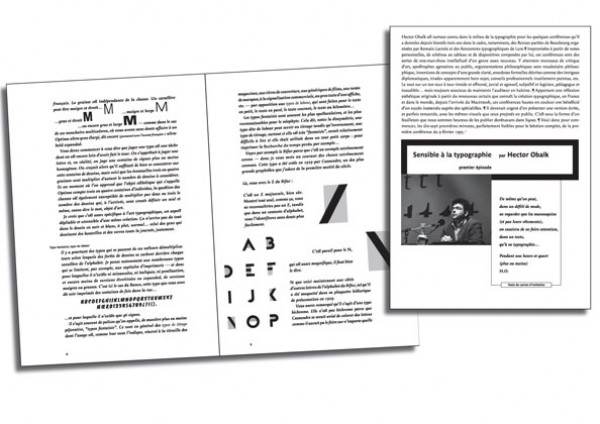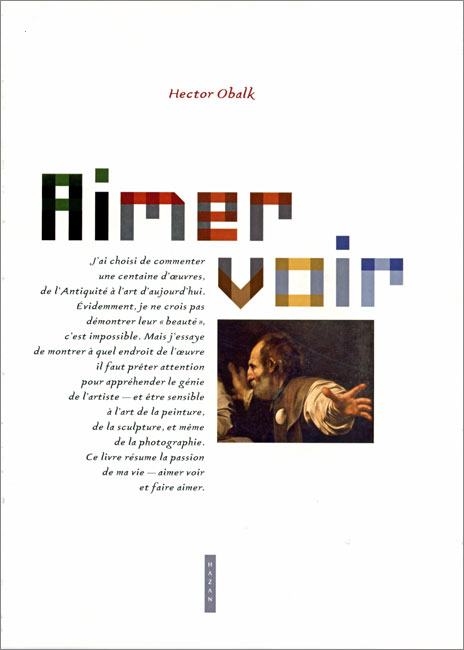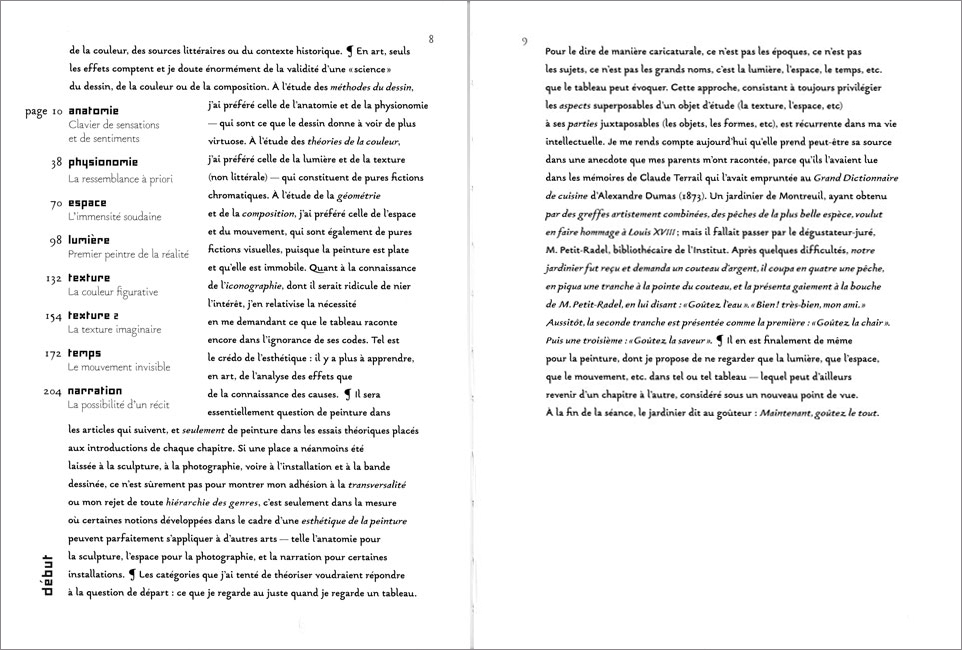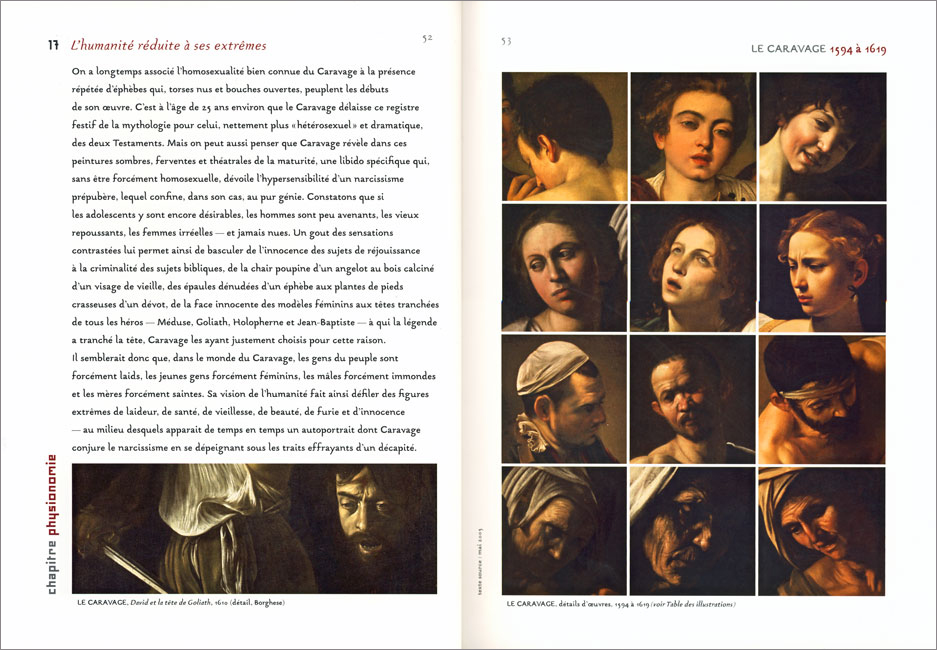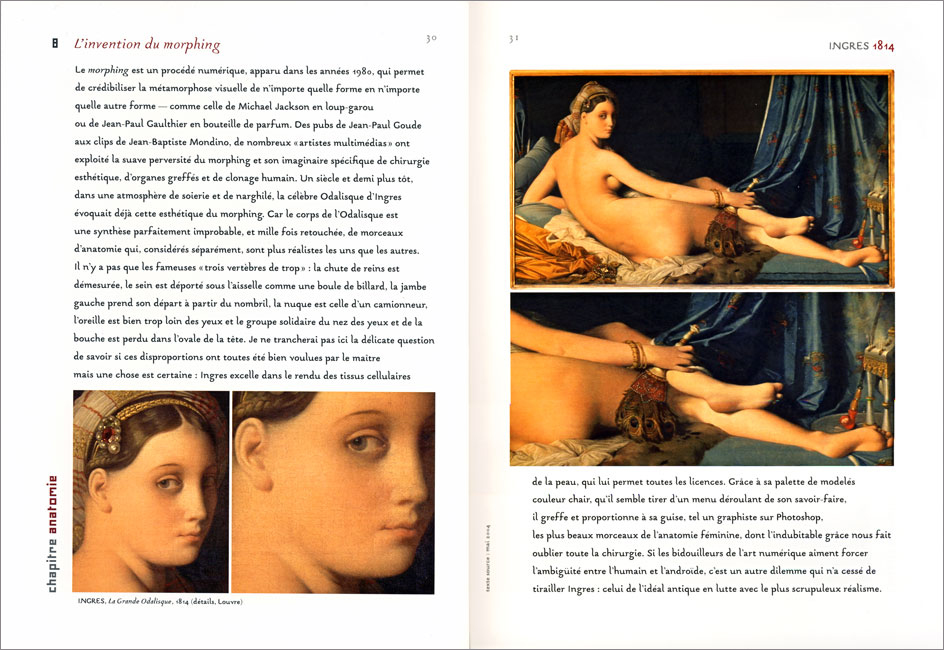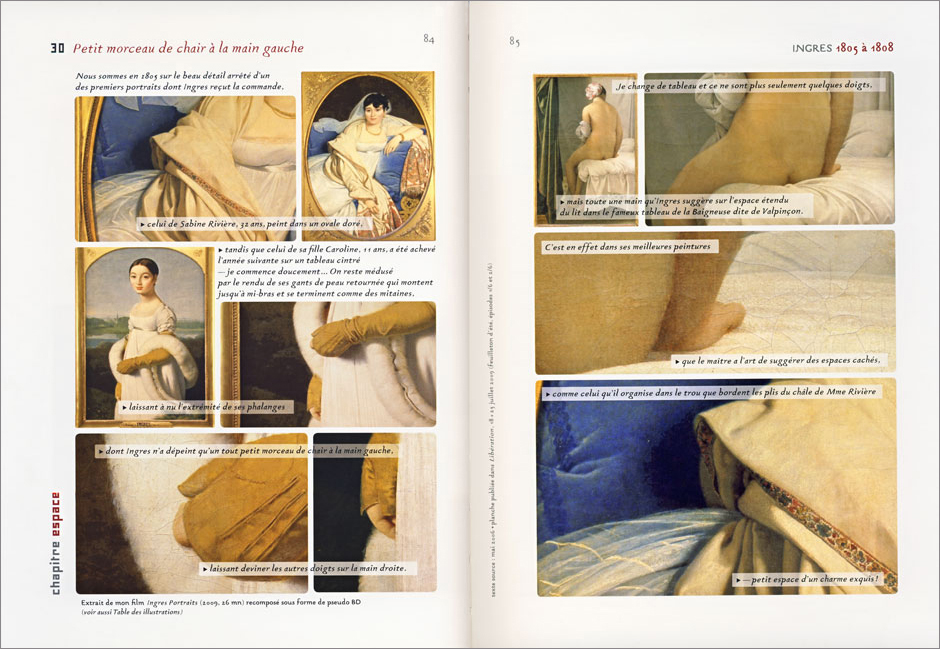
Pense-bête typo avant impression ou l’art du “rechercher/remplacer”.
C’est la période de bouclage des diplômes dans les écoles d’art ; voici donc un pense-bête typo pour aider les étudiants.
règles d’or pour la compo :
1. pour la composition en drapeau, on supprime les césures : le drapeau en sera naturellement plus rythmé, donc plus beau. On essaie au maximum de faire les retours lignes en fonction de la syntaxe, ce qui aide à la lecture et à l’accès au sens. On contournera cette règle sur de toutes petites largeurs de colonnes, (type news, infos, etc.) où il est préférable de mettre des césures afin de ne pas se retrouver avec des lignes de 2 ou 3 mots, un peu ridicules et très désagréables à lire.
2. en-dessous de 45 signes par lignes (c’est une moyenne bien sûr) on est obligé de composer en drapeau, sinon on se retrouve avec plein de trous et lézardes qu’il est impossible de corriger, que l’on soit bon ou pas, expérimenté ou pas.
3. dans les compositions justifiées on vérifie ses césures si on ne les a pas modifiées par défaut dans son application (je rappelle : 6/3/3 ou 7/4/3 et non 5/2/3) et si possible on respecte la célèbre règle du “concuvit”.
4. On choisit entre le saut de ligne et le refoncement d’alinea qui signifient la même chose et ne doivent donc pas être utilisés ensemble. Si l’on choisit le renfoncement, on le supprime au premier paragraphe, car le lecteur ici n’a pas besoin d’indication, le début c’est le début, il comprend.
règles d’or pour la micro typo :
1. les faux guillemets et fausses apostrophes.
Les guillemets dits américains ne sont pas de vrais guillemets, ils servent à noter les secondes, tout comme la fausse apostrophe sert à indiquer les minutes. On les supprime et on les remplace par les guillemets français ou anglais, et par les vraies apostrophes.
2. les espaces avant/après les signes de ponctuation.
3. les ligatures linguistiques (obligatoires) : ce sont les œ, æ, Æ, et Œ.
4. les ligatures esthétiques,
c’est-à-dire les
ne sont pas indispensables à la bonne écriture de la langue, mais indispensables au bel ouvrage typographique.
Les
plus rares, forment la seconde catégorie de ces ligatures esthétiques. Elles ne sont disponibles que dans certaines fontes seulement. Les utiliser ou pas est alors un choix personnel du typographe.
5. les petites capitales.
Les numéros des siècles se composent en chiffres romains et en petites capitales lorsque c’est possible. Attention aux fausses petites capitales vraiment laides ; beaucoup trop maigres elles sautent aux yeux et heurtent la lecture. Alors quand on n’en a pas, ce n’est pas grave, on fait sans mais on ne fait pas croire qu’on en a.
6. l’accentuation les capitales : oui je suis pour – définitivement (je pense que Vincent CONNARÉ, créateur du Comic Sans, trouve également cela très important). Cela relève du domaine de l’orthographe ; aucune limitation technique n’empêche aujourd’hui de le faire.
7. les chiffres bas de casse. S’ils sont disponibles dans la fonte, les employer dans le texte courant amène souplesse et élégance. Là aussi, ce n’est pas une règle mais un choix personnel.
8. les abréviations.
Il est courant de se tromper dans les abréviations des nombres ordinaux. Il faut retenir les règles suivantes :
Pour les mots se terminant par la lettre “o”, il faut veiller à utiliser le  “o ” en lettre supérieure et non le petit ° du clavier qui sert à noter les degrés.
Pour rappel :
Les vraies lettres supérieures sont dessinées spécialement et sont incluses dans la fonte. Si ce n’est pas le cas et que la fonte choisie n’en comporte pas, il est possible de créer des fausses lettres supérieures et de choisir leur taille dans les Préférences/Caractères d’XPress, ou Préférences/Texte avancé/d’InDesign (dans ce dernier, les exposants et les lettres supérieures ne sont pas différenciés). Contrairement aux petites capitales, la tricherie proposée par les applications est tout à fait acceptable.
9. les italiques : il faut les utiliser pour les titres d’œuvres et les locutions d’origine étrangère, c’est fondamental pour le confort de lecture.
Tous ces conseils sont extraits du Petit Manuel de composition typographique. Ils sont valables pour le print. Pour le web, je n’ai pas encore trouvé les astuces pour respecter les règles de la belle composition et je m’énerve souvent sur ce blog, je l’avoue, pour essayer de faire au mieux. J’y travaille cet été, promis !
Tracés régulateurs, grilles et gabarits, la conquête de la liberté & de l’harmonie.
Il (le typographe) doit inlassablement parfaire son sens des proportions, afin de pouvoir juger sans défaillance de la portée et de la limite d’un rapport de proportions. Il sentira alors à quel moment la tension établie entre deux éléments devient si forte que l’harmonie se trouve menacée. Il apprendra à éviter les rapports sans tension aucune qui engendrent l’uniformité et l’ennui. Il déterminera en outre le degré de tension plus ou moins fort qui devra exister selon la nature et le caractère de l’ouvrage qui lui est confié. On ne peut donc concevoir un principe de calcul rigide, comme le rapport de la règle d’or 3  : 5 ou 8  : 13, car ce rapport peut être valable pour un travail et faux pour un autre. Emil Ruder, Typographie, 1967, p. 92.*